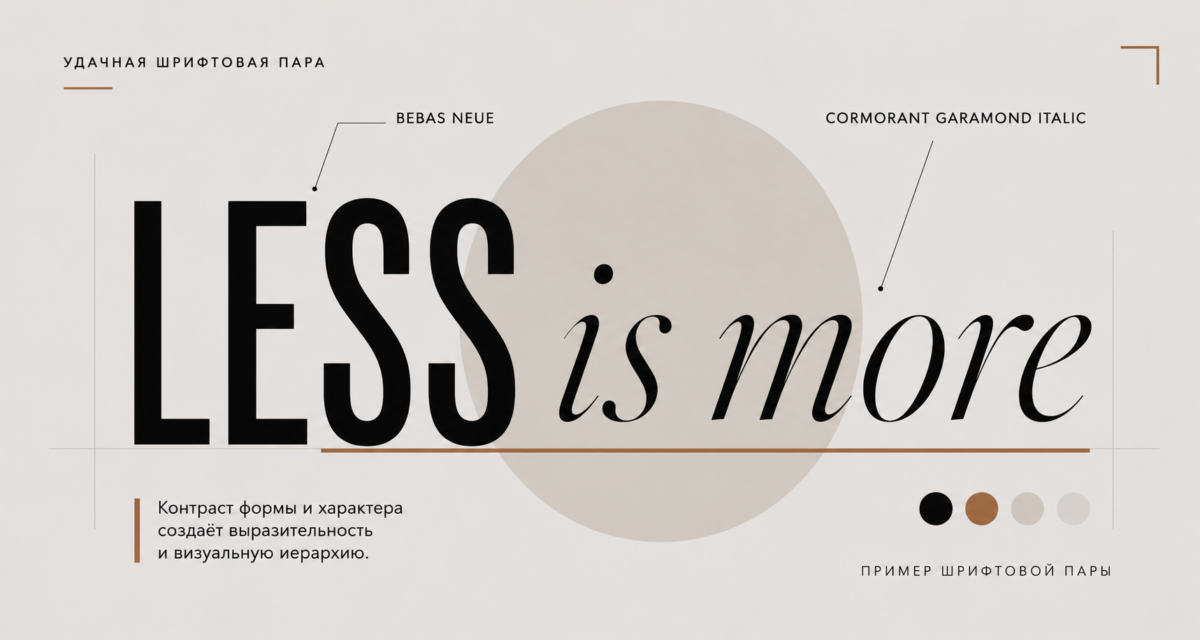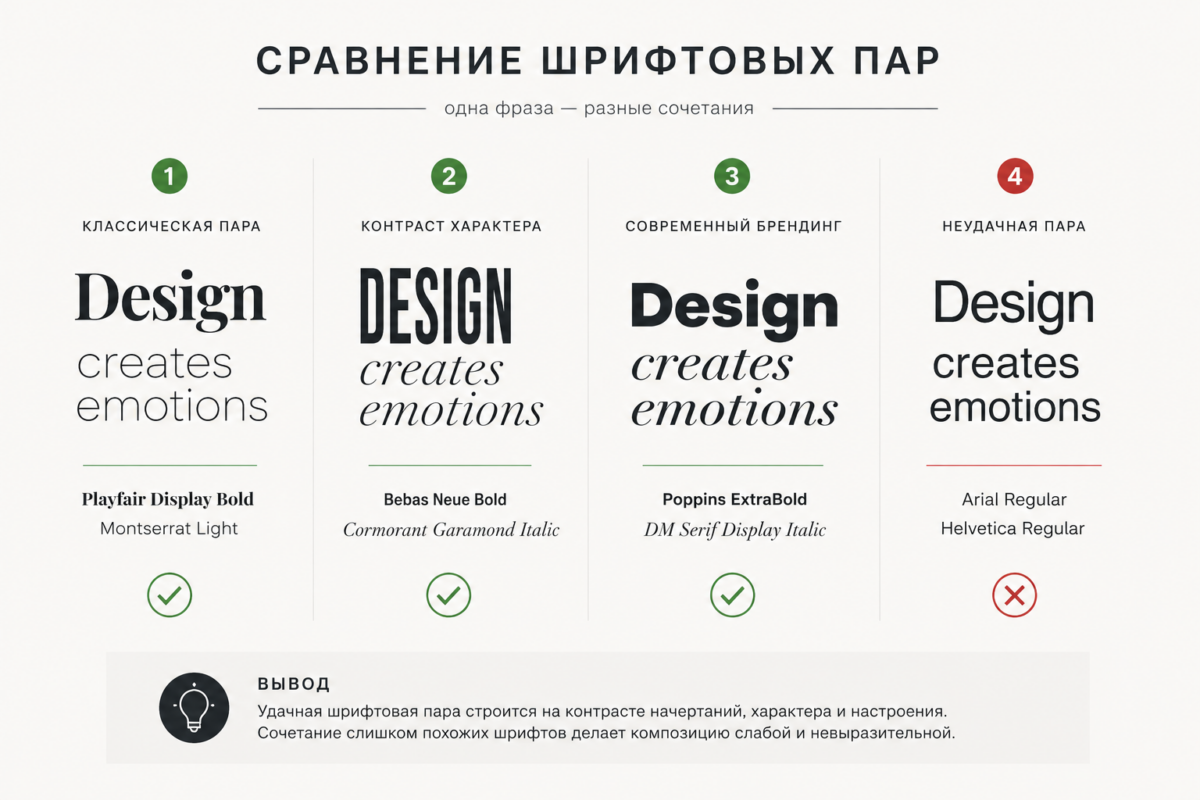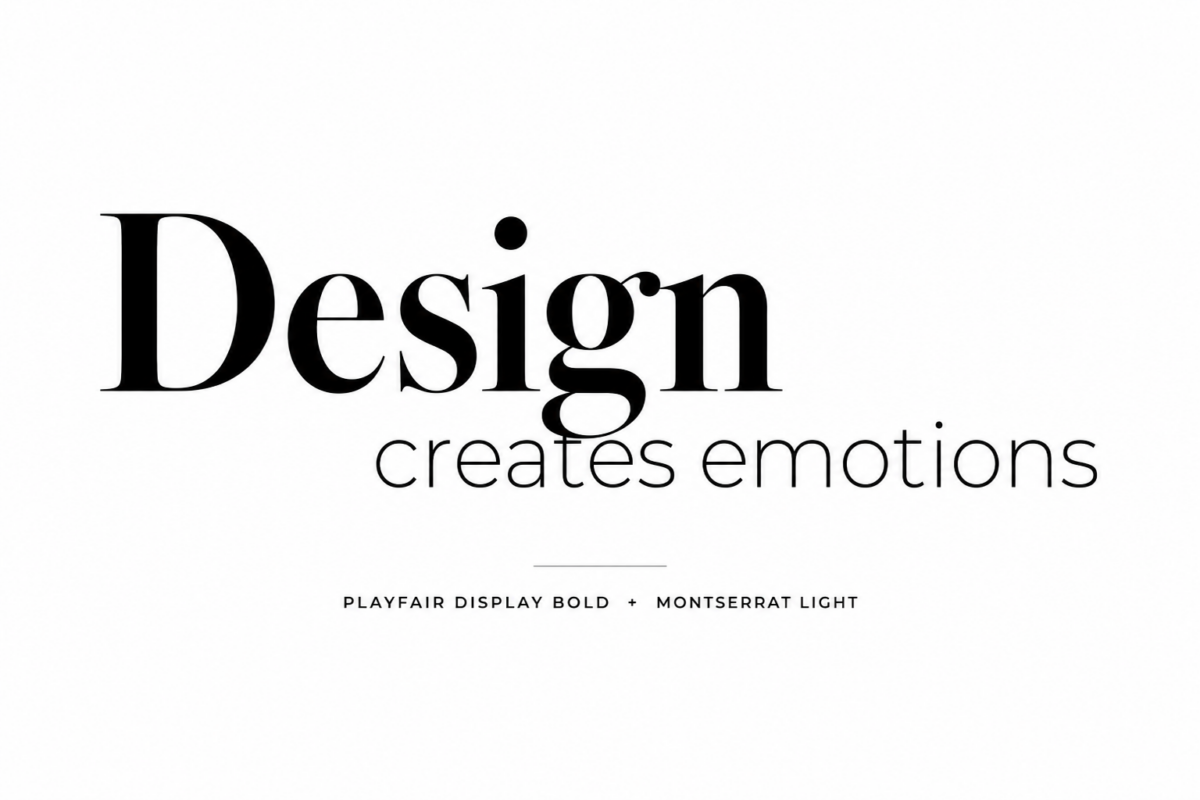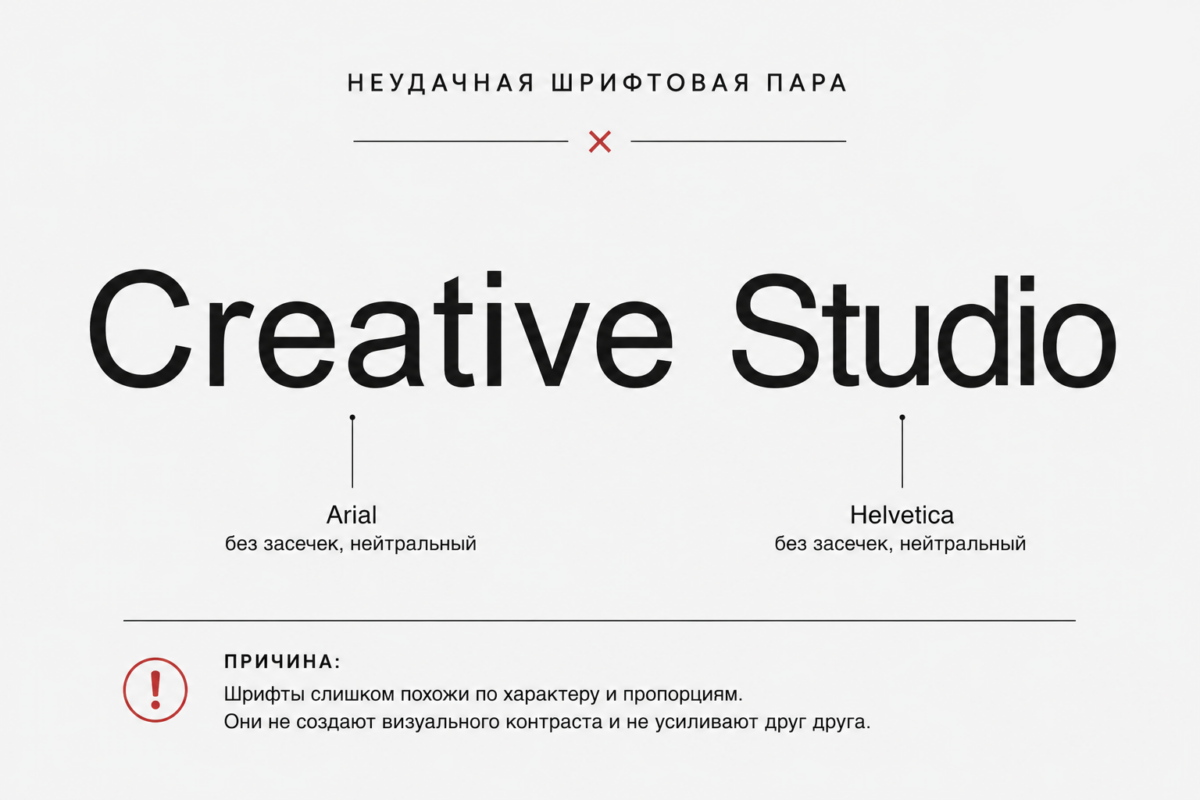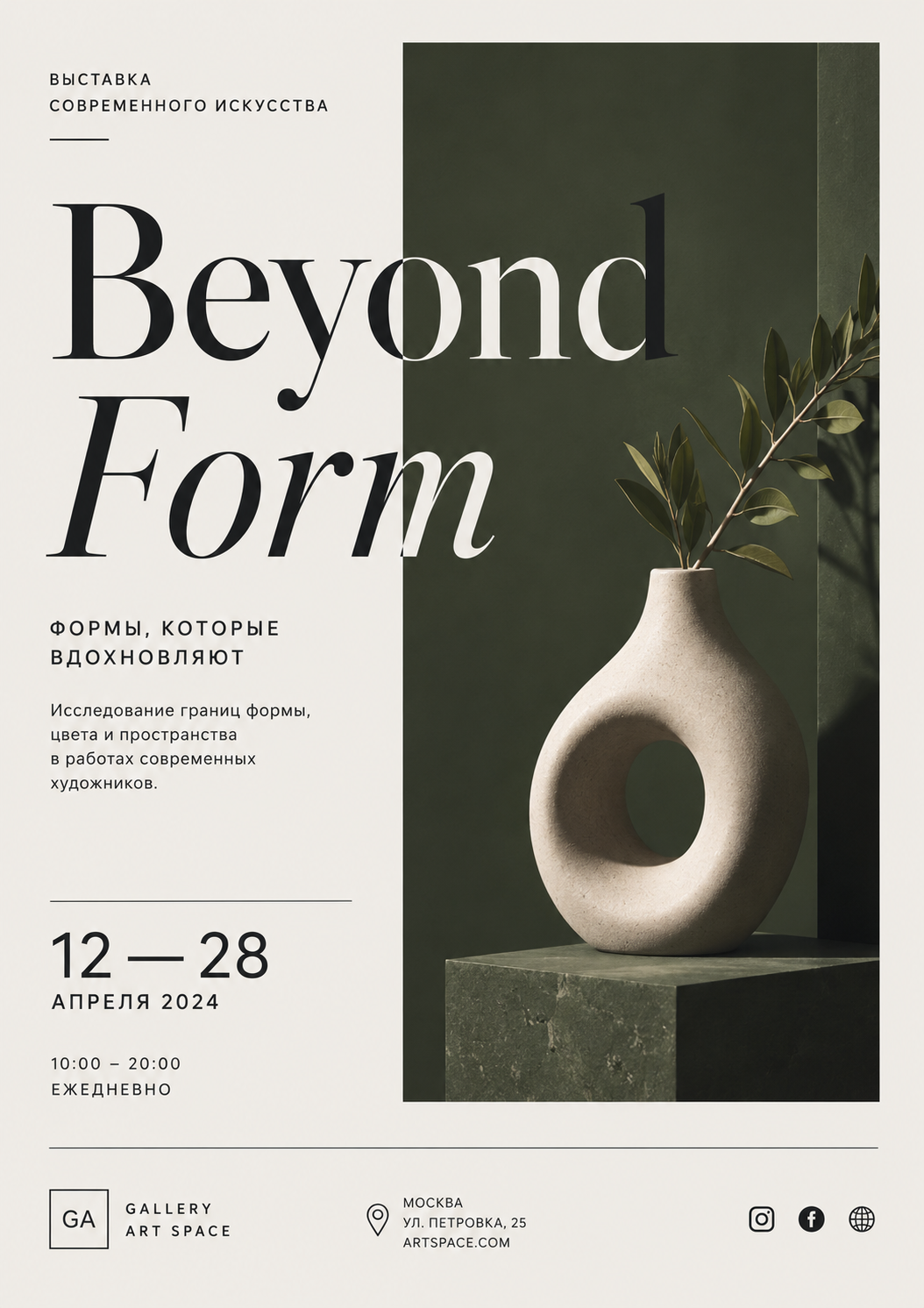
Шрифт является одним из важнейших инструментов визуальной коммуникации. Он способен передавать настроение бренда, формировать первое впечатление о компании и влиять на удобство восприятия информации. Даже самый качественный макет может потерять свою эффективность, если дизайнер неправильно подберёт типографику.
Одним из базовых навыков графического дизайнера считается умение создавать шрифтовые пары. Под этим термином понимается сочетание двух или нескольких шрифтов, которые используются в одном проекте и дополняют друг друга. Правильно подобранная пара помогает выстроить визуальную иерархию, сделать дизайн более профессиональным и облегчить чтение текста.
Шрифтовая пара — это комбинация гарнитур, которые используются для разных уровней информации в одном проекте. Как правило, один шрифт применяется для заголовков, а второй — для основного текста.
Например, на упаковке продукта название бренда может быть выполнено выразительным акцентным шрифтом, а состав и техническая информация — нейтральным и хорошо читаемым гротеском.
Основная задача шрифтовой пары заключается в создании баланса между контрастом и единством. Если шрифты слишком похожи, дизайн становится скучным и однообразным. Если различия слишком велики, возникает ощущение хаоса.
По данным исследований в области UX-дизайна, пользователи оценивают визуальное качество макета в течение первых секунд после просмотра. Одним из факторов такой оценки является типографика.
Грамотное использование шрифтов позволяет:
Не случайно крупные бренды уделяют большое внимание выбору корпоративных шрифтов и разработке типографической системы.
Перед созданием шрифтовой пары необходимо понимать основные категории гарнитур.
Классические гарнитуры, имеющие небольшие декоративные элементы на концах букв.
Примеры:
Такие шрифты ассоциируются с надёжностью, традициями и экспертностью.
Шрифты без засечек. Сегодня они особенно популярны в цифровой среде.
Примеры:
Гротески воспринимаются как современные, технологичные и универсальные.
Имитируют почерк человека.
Используются для:
Применять такие шрифты следует осторожно, поскольку они часто ухудшают читаемость.
Создаются для привлечения внимания и обычно используются только в заголовках.
Они помогают создать уникальный визуальный образ, но редко подходят для больших текстовых массивов.
Контраст является основой хорошей типографики.
Самое распространённое решение — сочетание шрифта с засечками и гротеска.
Например:
Заголовок — Playfair Display
Основной текст — Montserrat
Подобное сочетание позволяет визуально разделить уровни информации и сделать композицию более выразительной.
Несмотря на различия, шрифты должны выглядеть как часть одной системы.
Например, строгий минималистичный гротеск будет плохо сочетаться с декоративным шрифтом в винтажном стиле.
При выборе гарнитур важно учитывать:
Новички часто стремятся использовать как можно больше гарнитур, считая это способом сделать дизайн интереснее.
На практике большинство профессиональных проектов используют:
Большое количество гарнитур усложняет восприятие информации и разрушает визуальную целостность.
Одна из самых популярных комбинаций для брендинга и рекламы.
Преимущества:
Подходит для статей, блогов и корпоративных сайтов.
Сочетание обеспечивает высокий уровень читаемости даже при большом объёме текста.
Часто используется в рекламных материалах и афишах.
Крупный выразительный заголовок эффективно привлекает внимание пользователя.
Упаковка требует особого подхода к типографике.
Покупатель принимает решение о покупке за несколько секунд, поэтому информация должна считываться максимально быстро.
На упаковке обычно выделяют несколько уровней текста:
Для каждого уровня подбирается соответствующее типографическое решение.
В премиальном сегменте часто используются минималистичные шрифтовые системы с большим количеством свободного пространства. В массовом сегменте акцент делается на крупные заголовки и высокую заметность на полке магазина.
Если различия между гарнитурами минимальны, пользователь может не заметить структуру текста.
Когда заголовки и основной текст выглядят одинаково, информация воспринимается значительно хуже.
Красивый декоративный шрифт может хорошо выглядеть в названии, но практически всегда создаёт проблемы при наборе больших текстов.
Некоторые дизайнеры ставят эстетику выше удобства пользователя. В результате текст становится сложным для восприятия.
Перед началом работы полезно ответить на несколько вопросов:
После этого можно подобрать несколько вариантов шрифтовых пар и протестировать их в реальном макете.
Шрифтовая пара является важным инструментом графического дизайна. Именно типографика помогает организовать информацию, создать визуальную иерархию и передать характер бренда.
Умение грамотно сочетать шрифты приходит с практикой, однако знание базовых принципов значительно упрощает процесс проектирования. Хорошая шрифтовая пара делает дизайн не только красивым, но и эффективным, а значит помогает решать задачи бизнеса и улучшать пользовательский опыт.